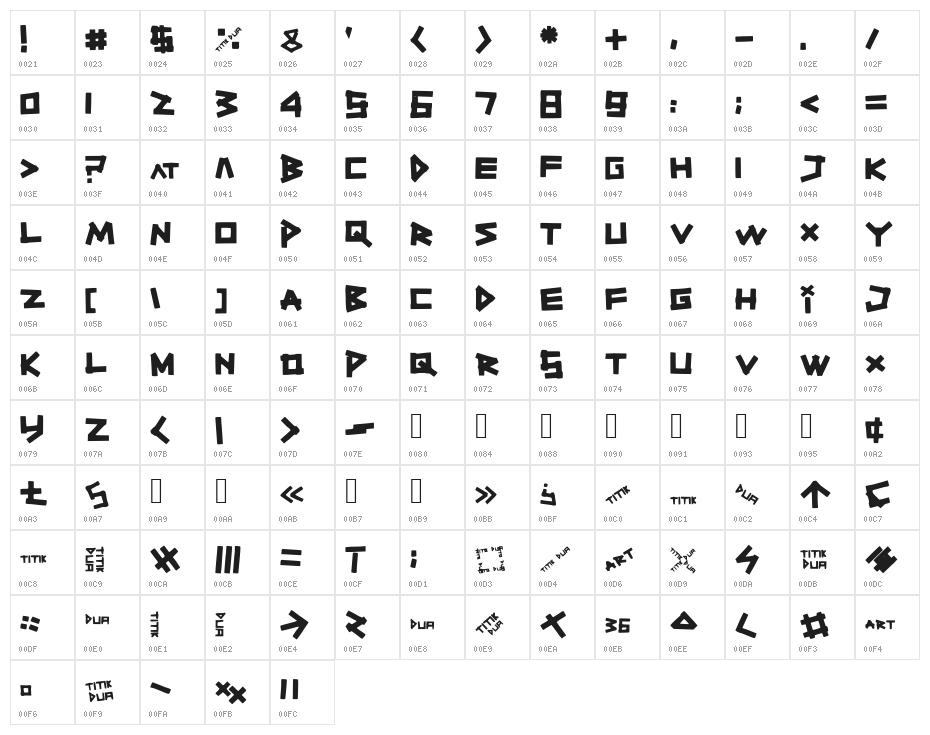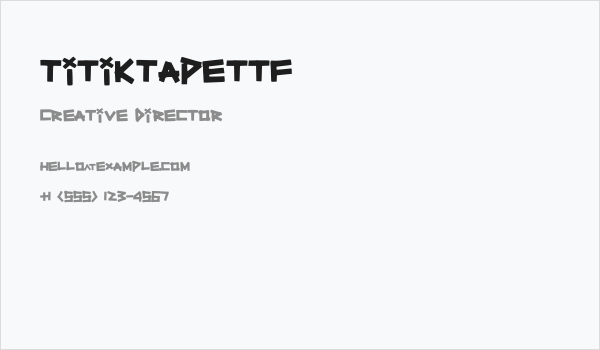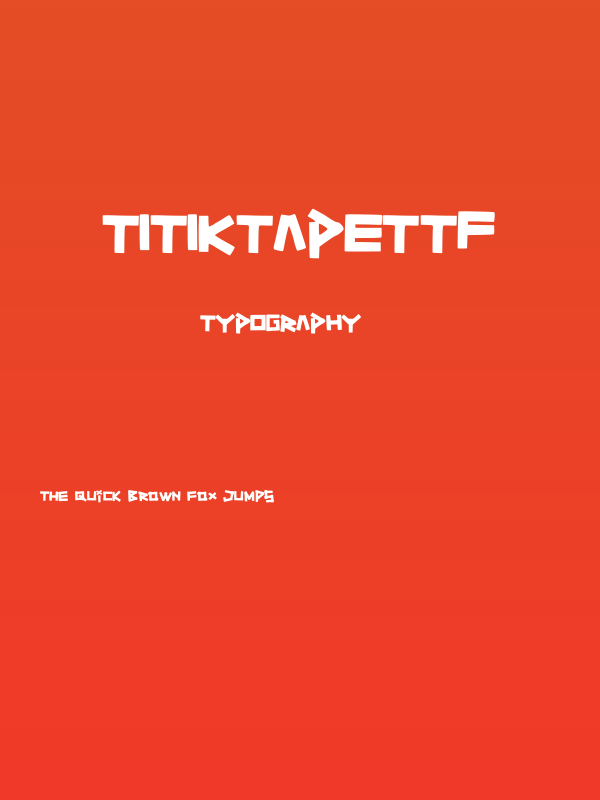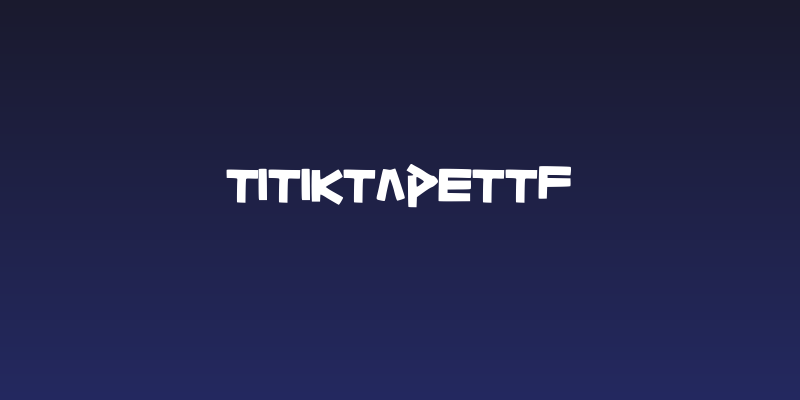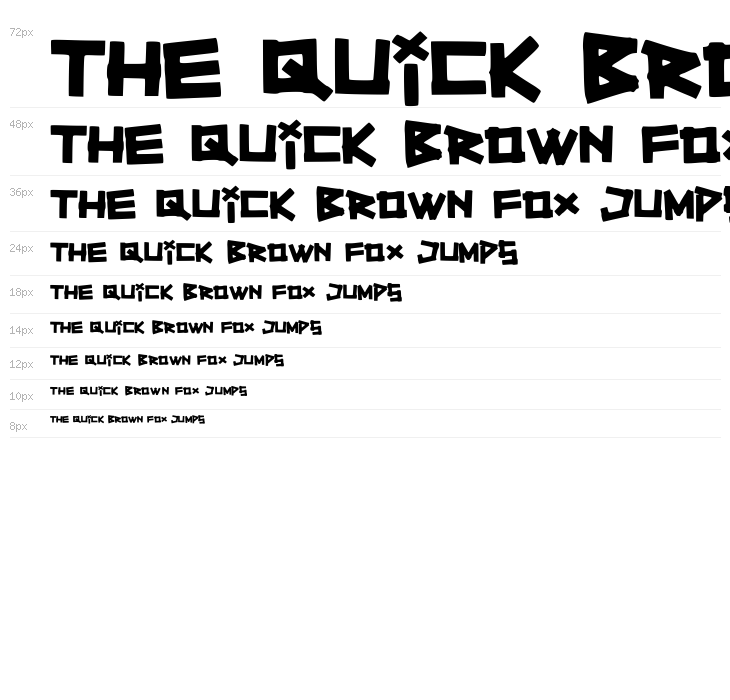
TitikTapettf Font
| النمط العام | Modern, Urban, Edgy |
| مشاريع مقترحة | Ideal for street art designs, music album covers, urban-themed posters, and edgy branding projects. |